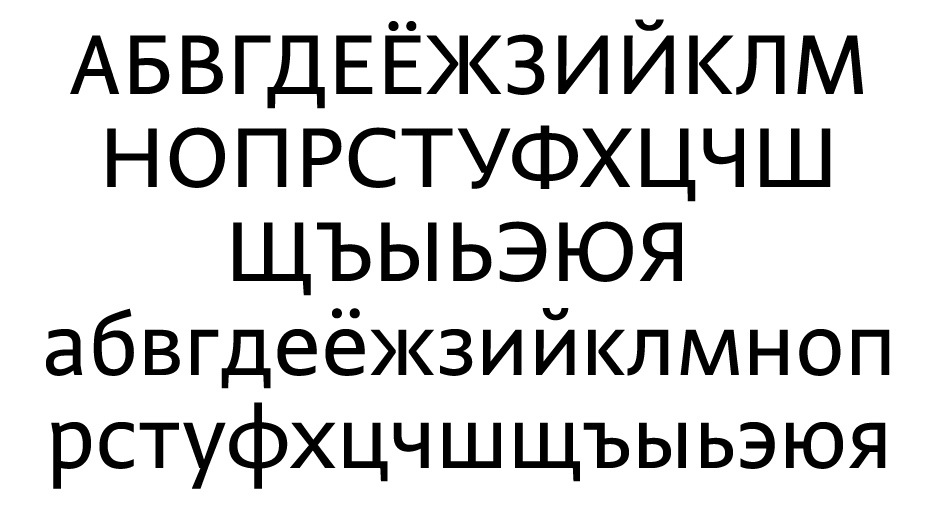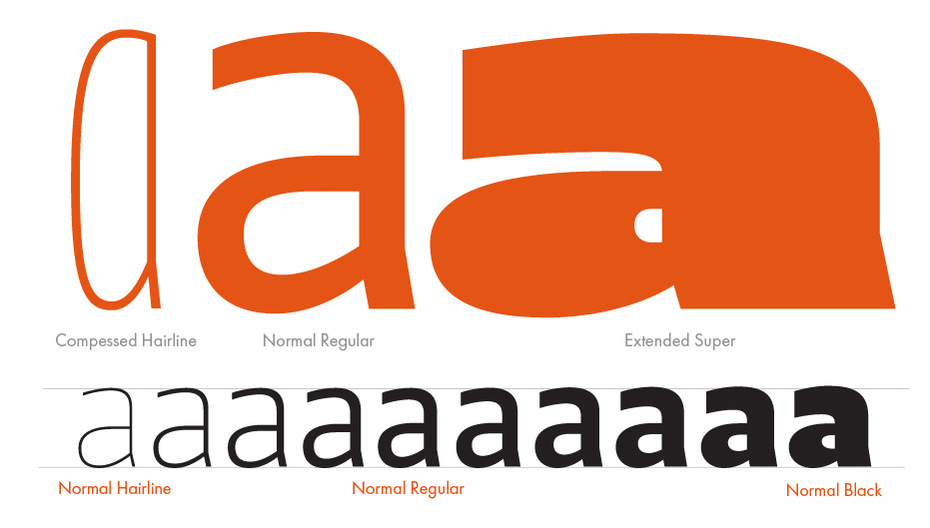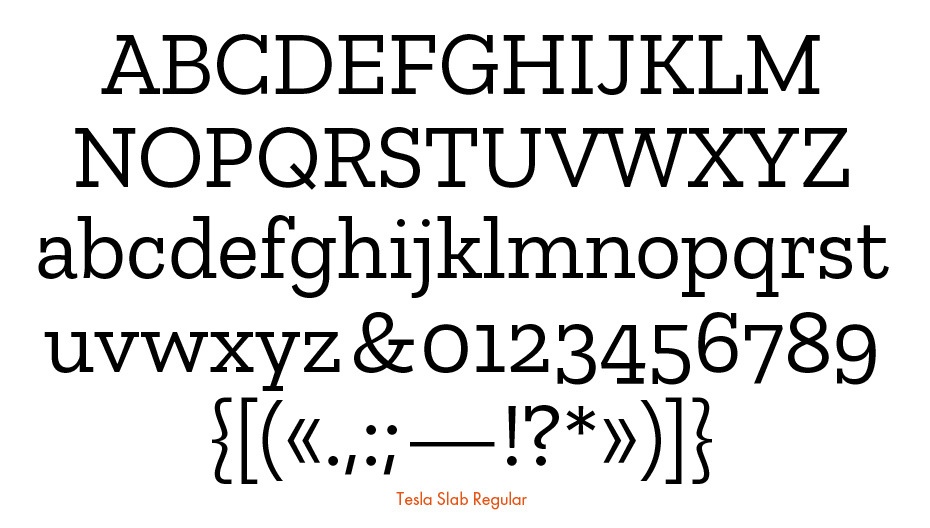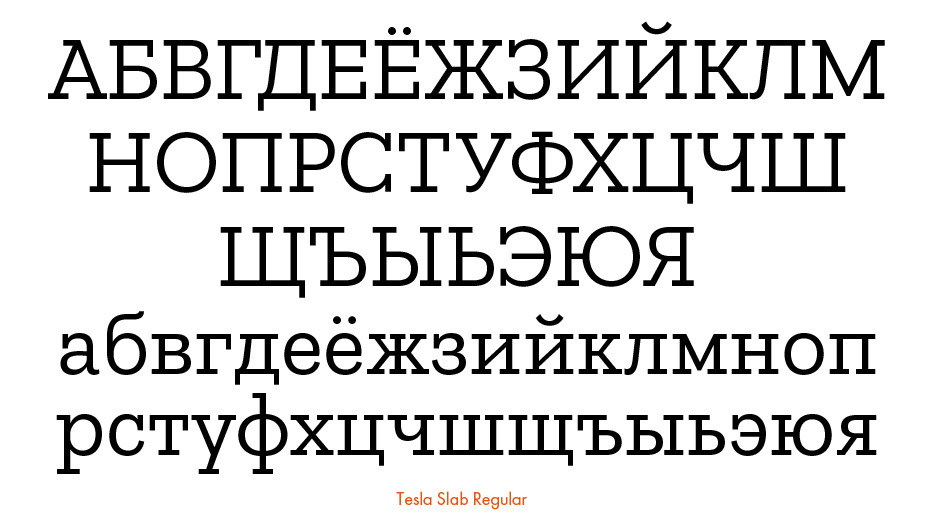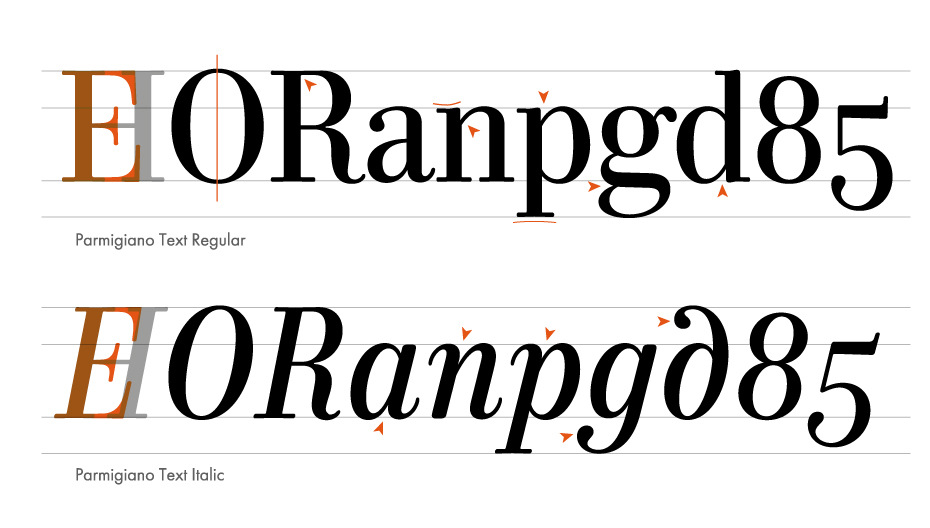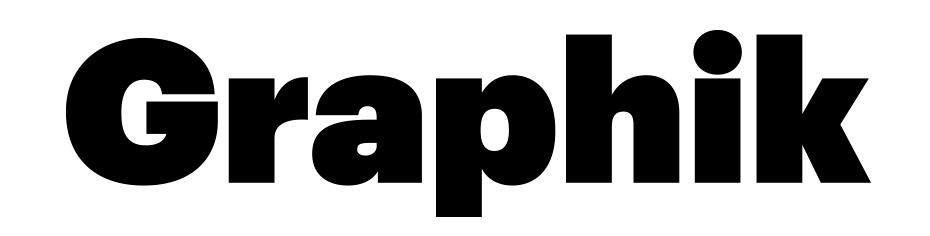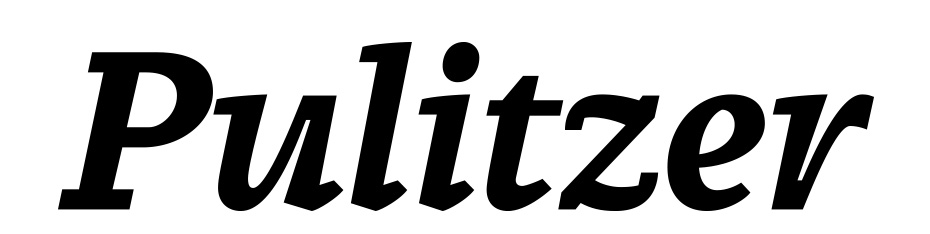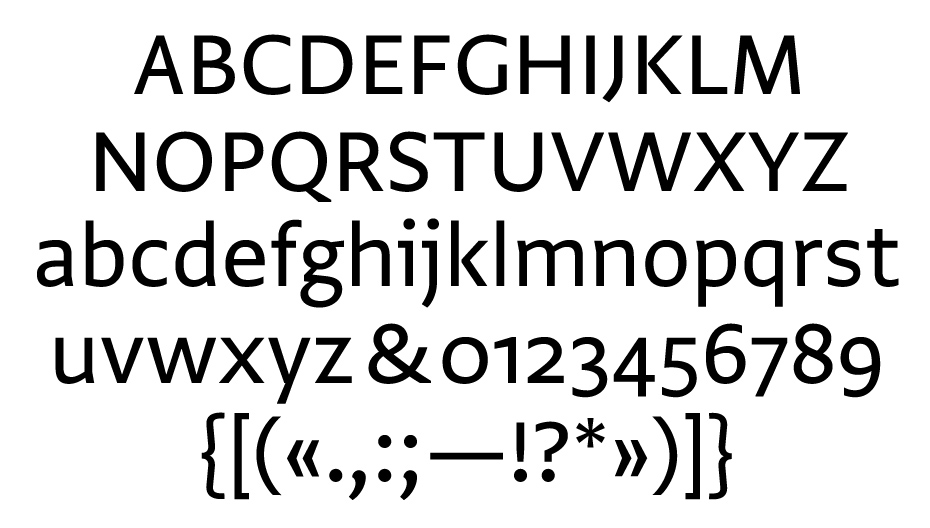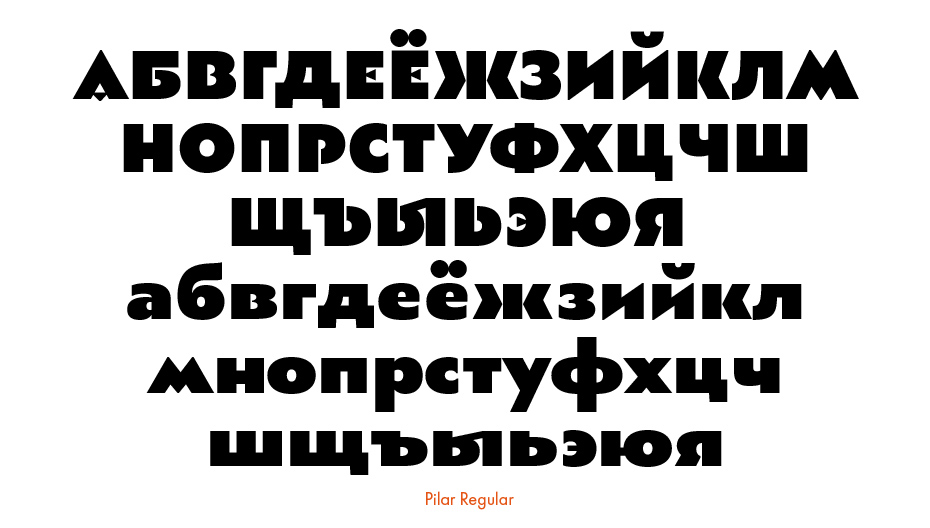
Десять шрифтов с кириллицей 2015 года, о которых мы хотим поговорить сегодня
Де­сять шриф­тов с ки­рил­ли­цей 2015 го­да,
о ко­то­рых мы хо­тим по­го­во­рить се­го­дня
Мы ре­ши­ли уб­рать из на­зва­ния на­ше­го еже­год­но­го об­зо­ра сло­во «топ». Опыт по­след­не­го от­бо­ра фи­на­ли­стов при­внёс в ред­кол­ле­гию — кро­ме жар­ко­го об­су­жде­ния и ка­те­го­ри­че­ских за­яв­ле­ний — по­ни­ма­ние, что эпи­тет «луч­ший», и уж тем бо­лее фра­за «луч­шая ки­рил­ли­ца», зву­чит край­не субъ­ек­тив­но и вы­со­ко­мер­но. «Луч­шее» не­про­из­воль­но тре­бу­ет по­лю­са «худ­шее», воз­бу­жда­ет со­мне­ния («до­ста­точ­но ли луч­шее?») и тре­бу­ет срав­не­ния «луч­ше, чем...». Да­бы из­бе­жать этих про­ти­во­ре­чий, мы со­сре­до­то­чи­лись на про­фес­си­о­наль­ном ин­те­ре­се к са­мо­му пред­ме­ту — шриф­ту как яв­ле­нию.
Сре­ди пред­став­лен­ных ни­же ра­бот есть шриф­ты-со­бы­тия, шриф­ты-па­ра­док­сы, шриф­ты-нео­фи­ты, шриф­ты-ве­те­ра­ны, шриф­ты-ма­ни­фе­сты, но объ­еди­ня­ет их клю­че­вой по­вод — же­ла­ние об­су­дить, рас­смот­реть, про­ве­рить в ра­бо­те и пред­ло­жить на суд чи­та­те­ля. В ито­ге бы­ли вы­бра­ны те шриф­ты, о ко­то­рых, на взгляд ре­дак­ции и ред­кол­ле­гии, есть смысл по­го­во­рить, — про­ек­ты, ко­то­рые ста­ли опре­делён­ным пре­це­ден­том по мне­нию на­блю­да­те­лей.
Из все­го мно­го­об­ра­зия шриф­тов с ки­рил­ли­цей про­шло­го го­да в пред­ва­ри­тель­ный от­бор по­па­ли 39 ра­бот. Од­на­ко, по на­шим на­блю­де­ни­ям, про­из­во­ди­тель­ность шриф­то­во­го це­ха для ши­ро­кой ауди­то­рии (не­смот­ря на уве­ли­че­ние ко­ли­че­ства шриф­то­вых ди­зай­не­ров) в про­шлом го­ду ед­ва ли вы­рос­ла. Усло­вия от­бо­ра лонг-ли­ста оста­лись не­из­мен­ны­ми: шрифт дол­жен со­дер­жать на­бор ки­рил­ли­че­ских зна­ков, пра­во на его ис­поль­зо­ва­ние долж­но быть до­ступ­но для при­об­ре­те­ния лю­бо­му же­ла­ю­ще­му, а да­та вы­пус­ка — не ра­нее ян­ва­ря и не по­зд­нее де­ка­бря 2015 го­да. Итак, 10 из 39 пе­ред ва­ми.
Ди­зай­нер Юрий Гор­дон. Из­да­тель: Юрий Гор­дон, Рос­сия
BazaArt
Ак­ци­дент­ный шрифт BazaArt был со­здан в 2013 го­ду для при­ло­же­ния Art рос­сий­ской ре­дак­ции жур­на­ла о мо­де Harper’s Bazaar (из­да­тель­ский дом Sanoma Independent Media). Это тот слу­чай, ко­гда шрифт, сде­лан­ный по за­ка­зу, экс­клю­зив­но при­ме­ня­ет­ся не­сколь­ко лет из­да­тель­ством, а за­тем пра­во на его ис­поль­зо­ва­ние вы­хо­дит в пуб­лич­ную про­да­жу. По по­доб­но­му сце­на­рию в 2014 го­ду был вы­пу­щен Domaine Sans Display Кри­са Со­вер­сби (Kris Sowersby) схо­жей эсте­ти­ки, ко­то­рый де­бю­ти­ро­вал в при­ло­же­нии New York Magazine Fashion Spring.
Ве­ро­ят­но, если по­пы­тать­ся вы­яс­нить, ка­кие шриф­ты в со­зна­нии ря­до­во­го по­тре­би­те­ля букв (не ди­зай­не­ра) счи­та­ют­ся кра­си­вы­ми, то имен­н­но та­кие шриф­ты мак­си­маль­но по­дой­дут для по­доб­ной ха­рак­те­ри­сти­ки. Ак­тив­ный кон­траст в со­че­та­нии с изящ­ны­м ро­счер­ко­м да­ют бес­про­иг­рыш­ное зри­тель­ное пе­ре­жи­ва­ние, будь то не­мец­кая фрак­ту­ра или на­ряд­ные кур­си­вы Кэз­ло­на.
С кон­ца XVIII ве­ка мак­си­маль­ный кон­траст стал стра­стью пу­ан­со­ни­стов и пе­чат­ни­ков, в по­го­не за тон­ким штри­хом со­вер­шен­ство­ва­лись тех­но­ло­гии и от­ли­ва­лись луч­шие сор­та бу­ма­ги. В на­ши дни вы­со­кий кон­траст в ти­по­гра­фи­ке стал не­отъ­ем­ле­мым эле­мен­том ин­ду­стрии мо­ды, ас­со­ци­и­ру­ясь с изыс­ком и эле­гант­ны­ми ма­не­ра­ми. Как пра­ви­ло, со сти­ли­сти­кой fashion ди­зай­не­ры при­вык­ли справ­лять­ся c по­мо­щью но­во­стиль­ных или ан­гло-шот­ланд­ских ан­тикв или же ис­поль­зуя шриф­ты с тон­ки­ми гео­мет­ри­че­ски­ми фор­ма­ми и эле­мен­та­ми ар-де­ко.
Ав­тор BazaArt иг­ра­ючи (эта ха­рак­те­ри­сти­ка под­хо­дит ко мно­гим ра­бо­там Юрия Гор­до­на) под­клю­ча­ет все па­ра­мет­ры: кон­траст, гео­мет­рич­ную утон­чён­ность, мо­ти­вы ти­по­гра­фи­ки 30-х. За счёт ва­ри­а­ций зна­ков — от уз­ких до ши­ро­ких с вы­ве­ден­ны­ми цир­ку­лем сво­ша­ми — ти­по­гра­фу пред­ла­га­ет­ся в каж­дом сло­ве на­хо­дить но­вые ком­би­на­ции. Каж­дая со­бран­ная та­ким об­ра­зом фра­за ста­но­вит­ся уни­каль­ной за счёт ва­ри­а­ций со­че­та­ния штри­хов.
BazaArt устро­ен так, что пе­ре­клю­че­ние ре­ги­стров меж­ду строч­ны­ми и про­пис­ны­ми зна­ка­ми мож­но ис­поль­зо­вать не столь­ко для обо­зна­че­ния на­ча­ла пред­ло­же­ния или имён соб­ствен­ных, сколь­ко для ин­то­ни­ро­ва­ния (ис­поль­зуя кла­ви­шу Shift как пе­даль фор­те­пи­а­но), фак­ти­че­ски по­лу­чая на­бор юни­кей­сом. При этом в кас­се шриф­та (че­рез па­лит­ру Glyphs) мож­но вы­брать ещё не­сколь­ко раз­лич­ных форм и про­пор­ций, вы­стра­и­вая вруч­ную не­об­хо­ди­мый ритм.
Строч­ные зна­ки име­ют ед­ва за­мет­ные вы­нос­ные эле­мен­ты, что вно­сит раз­но­об­ра­зие в вер­ти­каль­ный ритм на­бо­ра. Ки­рил­ли­ца в та­ком ис­пол­не­нии (и в сме­ше­нии форм обо­их ре­ги­стров) не толь­ко не усту­па­ет в пла­сти­ке и ха­рак­те­ре ла­ти­ни­це, но и обо­га­ща­ет её. Здесь мож­но най­ти как ком­пли­мен­ты ис­то­ри­че­ским фор­мам в бук­вах б, К, Ц, Щ, Э, Я, ко­то­рые раз­ви­ва­ют и уси­ли­ва­ют об­щую гра­фи­че­скую идею, так и ряд ки­рил­ли­че­ских ли­га­ту­р.
Ди­зай­нер Ва­си­лий Би­рю­ков. Из­да­тель: ParaType, Рос­сия
DIN 2014
Ис­то­рия шриф­та DIN на­чи­на­ет­ся в 1905 го­ду, ко­гда управ­ле­ние Ко­ро­лев­ски­ми прус­ски­ми же­лез­ны­ми до­ро­га­ми (Königlich Preußische Eisenbahn-Verwaltung) ре­ши­ло при­ве­сти к еди­но­му стан­дар­ту все над­пи­си на то­вар­ных ва­го­нах. Так по­явил­ся про­стой гео­мет­рич­ный шрифт, вы­чер­чен­ный по мо­дуль­ной сет­ке, ко­то­рый бы­ло не­слож­но вос­про­из­во­дить на ме­стах при по­мо­щи тра­фа­ре­та или от ру­ки. Поз­же он был адап­ти­ро­ван и для всех вы­ве­сок с на­зва­ни­я­ми же­лез­но­до­рож­ных стан­ций. По­сле по­ра­же­ния в Пер­вой ми­ро­вой вой­не пе­ред ру­ко­вод­ством Вей­мар­ской рес­пуб­ли­ки (в со­став ко­то­рой в 1918 го­ду во­шла Прус­сия) сто­я­ла за­да­ча объ­еди­не­ния раз­роз­нен­ных гер­ман­ских зе­мель, и клю­че­вую роль в этом от­во­ди­ли еди­ной транс­порт­ной си­сте­ме — Го­су­дар­ствен­ной же­лез­ной до­ро­ге (Deutsche Reichsbahn). Уни­фи­ка­ция и стан­дар­ти­за­ция име­ли и фи­нан­со­вое об­ос­но­ва­ние, осо­бен­но важ­ное для ослаб­лен­ной по­сле­во­ен­ной эко­но­ми­ки.
Со­би­ра­тель­ное на­зва­ние груп­пы ран­них ан­ти­квен­ных шриф­тов, осно­ван­ных на шриф­тах ве­не­ци­ан­ско­го ти­по­гра­фа и из­да­те­ля Аль­да Ма­ну­ция (Aldus Manutius, 1447–1515), ра­бо­ты бо­лон­ско­го гра­ве­ра Фран­че­ско Гриф­фо (Francesco Griffo, ок. 1450–1518) и па­риж­ско­го сло­во­лит­чи­ка Кло­да Га­ра­мо­на (Claude Garamond или Garamont, ок. 1490–1561). На­зва­ние «Га­раль­ды» озна­ча­ет шриф­ты, близ­кие к ГА­Ра­мо­ну и АЛЬ­Ду, и при­ду­ма­но оно фран­цуз­ским ис­сле­до­ва­те­лем ти­по­гра­фи­ки Мак­си­ми­ли­а­ном Вок­сом (Maximilien Vox) в 1954 г.